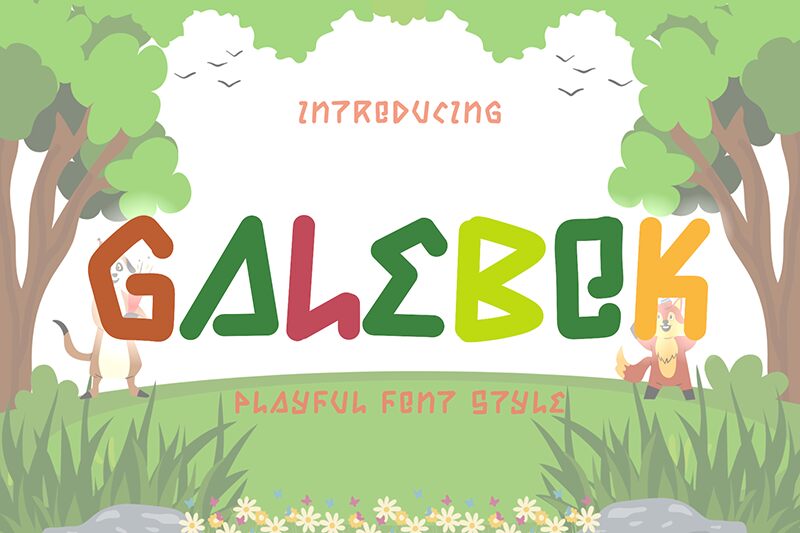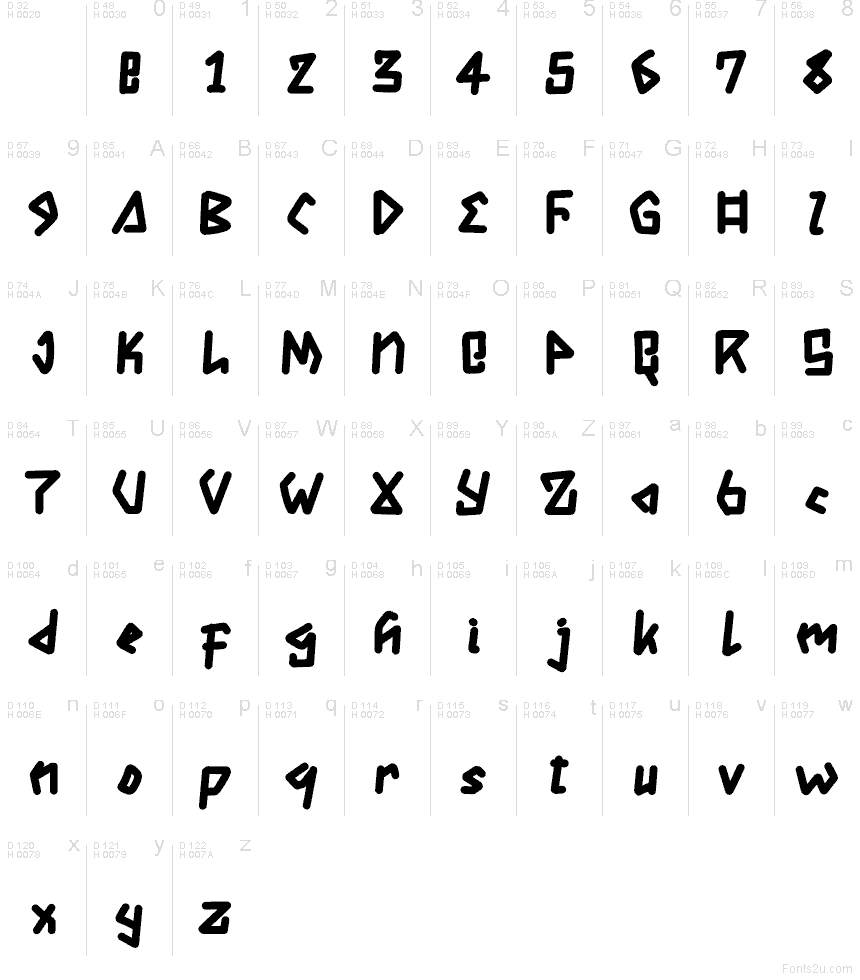
Galebok Demo
Galebok je bezplatné písmo typu display so zaoblenými, akoby ručne vyrezávanými tvarmi a ostrými uhlami, ktoré mu dodávajú rezbársky, mierne netradičný rytmus. Znaky pôsobia kompaktne a pevne, s mäkkými rohmi, naklonenými ťahmi a výraznými klinovitými detailmi, ktoré písmo robia dostatočne živým.
Galebok skvele funguje v nadpisoch plagátov, logách, grafike hier, letákoch či na obaloch všade tam, kde chcete, aby písmená vyzerali ako odtlačené a jedinečné. Tento bezplatný font je ideálny aj na krátke nápisy na merch či ako akcent v nadpisoch, pretože jeho nepravidelná geometria má dostatok charakteru na to, aby zaujala bez potreby ďalších dekorácií.